Шрифти красиві для powerpoint
Спасибі тобі величезне, за шрифти. Класичний шрифт з похилими літерами. Цікавий шрифт з тонкими буквами. Класні шрифти! Так, красиві українські шрифти це рідкість. 5. Ваші шрифти встановлені. Відмінні шрифти!
При створенні презентації PowerPoint на комп'ютері використовуються шрифти, які вже встановлені в системі. Відповідно, при підготовці презентації для демонстрації на інших комп'ютерах потрібно передбачити сумісність шрифтів.
- не використовуйте контур у фігур;
- не заливайте нічого градієнтом;
- пам'ятайте про шрифти.
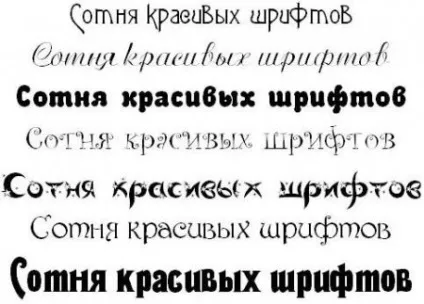
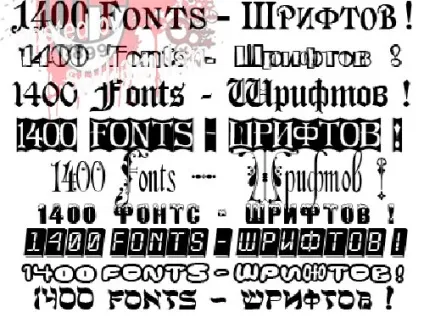
як зробити гарний шрифт в power point.
Дякуємо. Багато рукописних відмінних шрифтів. Де можна скачати (якщо вони існують) шрифти копіюють почерк Пушкіна та інших письменників і поетів? Дмитро, в цій збірці, як раз, є цей шрифт! Він так і називається.
Дякуємо! Весь мозок собі виніс, поки в інтернеті шукав кириличні рукописні шрифти. Зараз є крайня необхідність в розробці логотипу якраз з такими шрифтами.
Збереження шрифтів в PowerPoint
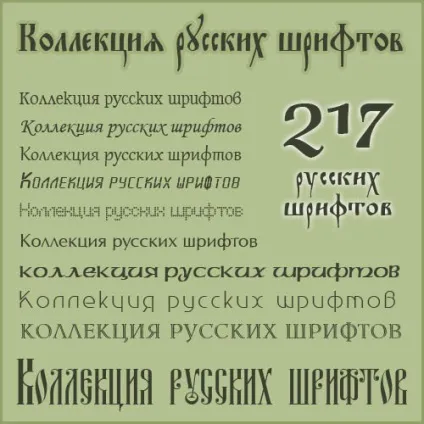
Які шрифти варто використовувати для створення презентацій
Шрифти, які ви використовуєте в Power Point не зроблять вашу презентацію успішної. Нижче кілька експертних думок про те, як вибрати правильний шрифт для вашої презентації (тип шрифту і його розмір), яку ви робите в Power Point або Keynote.
Найміть професіонала, виберіть шрифт, який би ви любили і зупиніться на ньому. Не міняйте шрифти з часом (хоча б не дуже часто) ... Правильно обраний шрифт стане немов вашим «почерком».
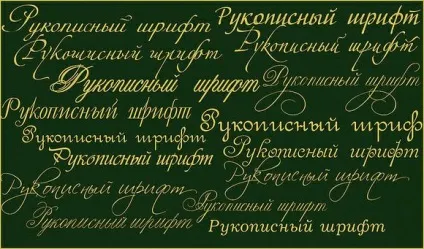
Для створення гарної презентації необхідні три складові - хороший текст зі структурою, добротна добірка зображень для слайдів і красивий шаблон PPT по темі бізнесу. При виборі шаблону Поверпойнт важливо звернути увагу на фон слайдів презентації.
Seth Godin рекомендує не використовувати шрифт Arial для презентацій. Ви завантажили красиві шрифти і використовували їх в створенні вашої презентації. Підкажіть, будь ласка шрифт в заголовках! Класичний шрифт, курсив. Друкарський шрифт із зарубками.